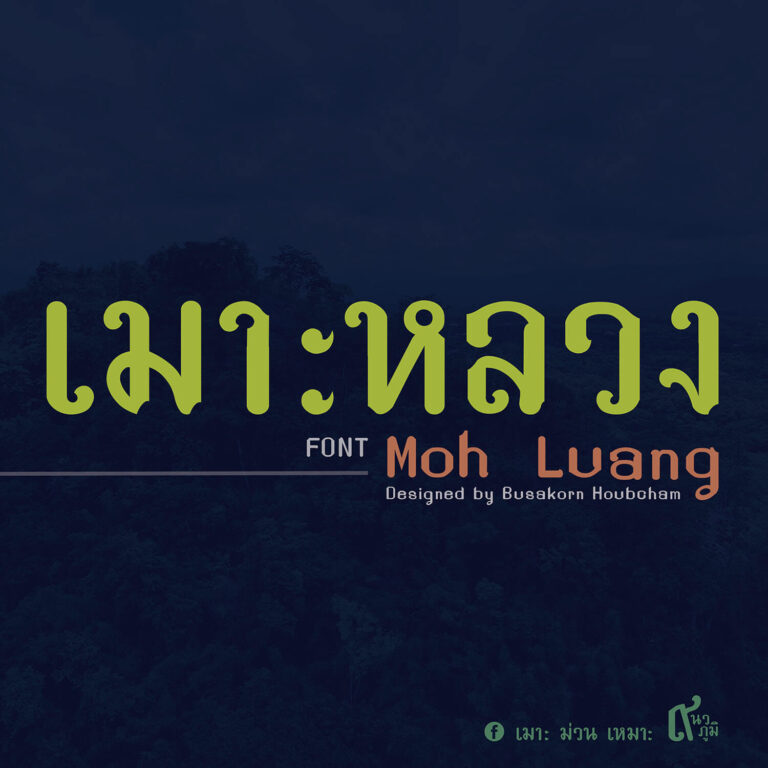
สร้างสรรค์ออกแบบตัวอักษรโดยมีต้นแบบจากป้ายวัดเมาะหลวงเดิม เป็นการต่อยอดจากภูมิหลังของประวัติศาสตร์ วัฒนธรรมของพื้นที่เดิม และส่งต่อด้วยการออกแบบมายังยุคสมัยปัจจุบัน เพื่อแสดงถึงอัตลักษณ์ของชุมชนบ้านเมาะหลวง อำเภอแม่เมาะ จังหวัดลำปาง